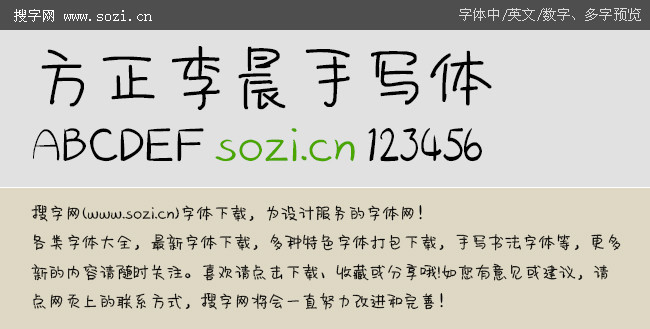
方正李晨手寫體
搜字網(wǎng)提供一款方正李晨手寫體字體下載,方正李晨手寫體是一款特色的手寫字體,由方正字庫(kù)出品,效果非常出色,適合應(yīng)用于海報(bào)設(shè)計(jì)、書籍排版、包裝設(shè)計(jì)等應(yīng)用。(本字體為個(gè)人非商用版,如需要商用請(qǐng)聯(lián)系方正公司購(gòu)買版權(quán))